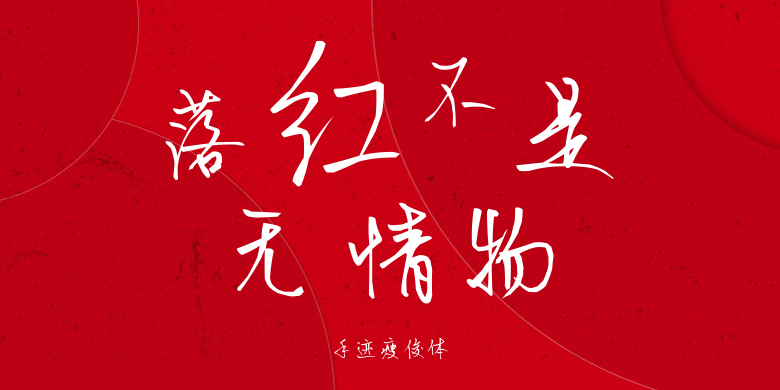
手迹瘦俊体
手迹瘦俊体,这款字体结构工整、笔画清晰,兼顾美观与易读性,适用于标题、正文、海报、包装、LOGO 等多种场景。字形优雅稳定,风格百搭耐看,适配日常排版与创意设计,让文字呈现更舒适、更具质感。手迹瘦俊体一笔一画,皆是细节,以均衡的比例、流畅的线条打造舒适视觉体验,字形端正大气,风格简约现代。无论是商业设计、品牌宣传还是日常排版,都能轻松驾驭,让文字更有格调与力量。手迹瘦俊体字体下载。